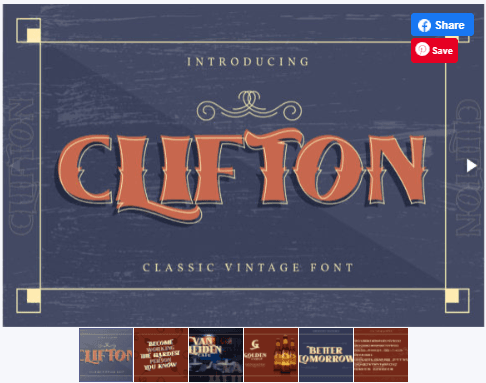
Clifton Font
Clifton - это черный шрифт, вдохновленный винтажными знаками и этикетками в стиле ретро. Это делает его идеальным и идеальным выбором для создания уникальных дизайнов, таких как плакаты, логотипы, этикетки, упаковка и многое другое!